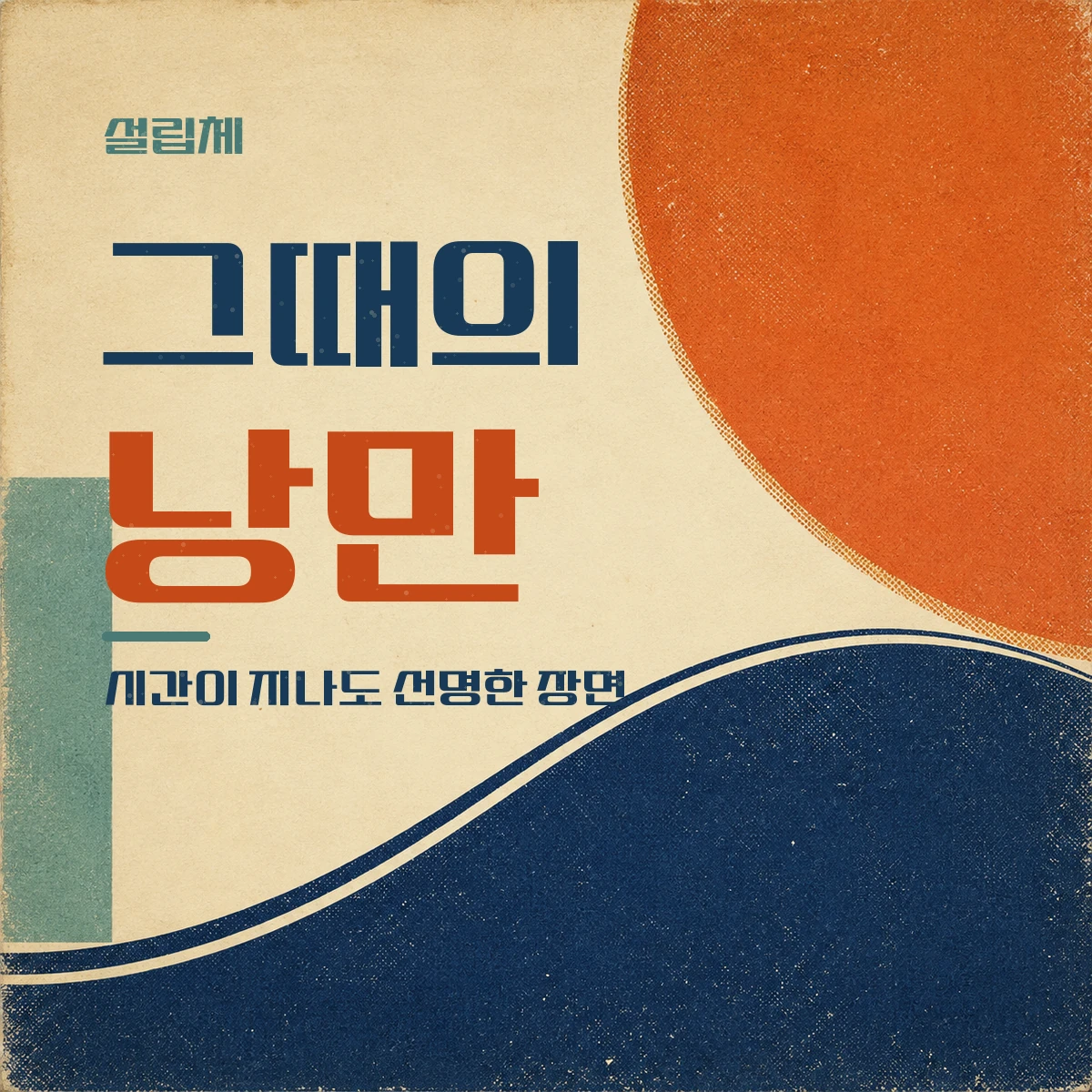
설립체 — 유건욱X폰트릭스에서 배포하는 무료 폰트입니다. 청소년이 서체 전문가에게 기초부터 배워 직접 그린, 단단하고 개성 있는 레트로 제목용 서체
이 서체에는 만든 사람의 사연이 있습니다. 서울시립청소년미디어센터 스스로넷이 2021년에 운영한 청소년디자인제작전문그룹 프로그램에서 청소년 유건욱이 만든 서체입니다. 청소년이 서체 전문가에게 기초부터 배워 자기 서체를 개발해 보는 진로 프로그램이었고, 그해 폰트릭스와 업무협약을 맺어 폰트릭스의 서체 디자이너가 직접 교육을 맡았습니다. 그해 다섯 종이 배포됐는데 그중 이 서체가 지상파와 유튜브에서 실제로 쓰이고 있다고 보도되기도 했습니다.
제작자가 직접 쓴 조형 설명은 남아 있지 않습니다. 영문 이름이 establish Retrosans인 것으로 보아 레트로 계열의 민부리로 스스로를 규정한 듯합니다. 파일에서 재어 보면 낱자가 가로로 넓게 퍼져 있고 한글은 2,782자입니다.